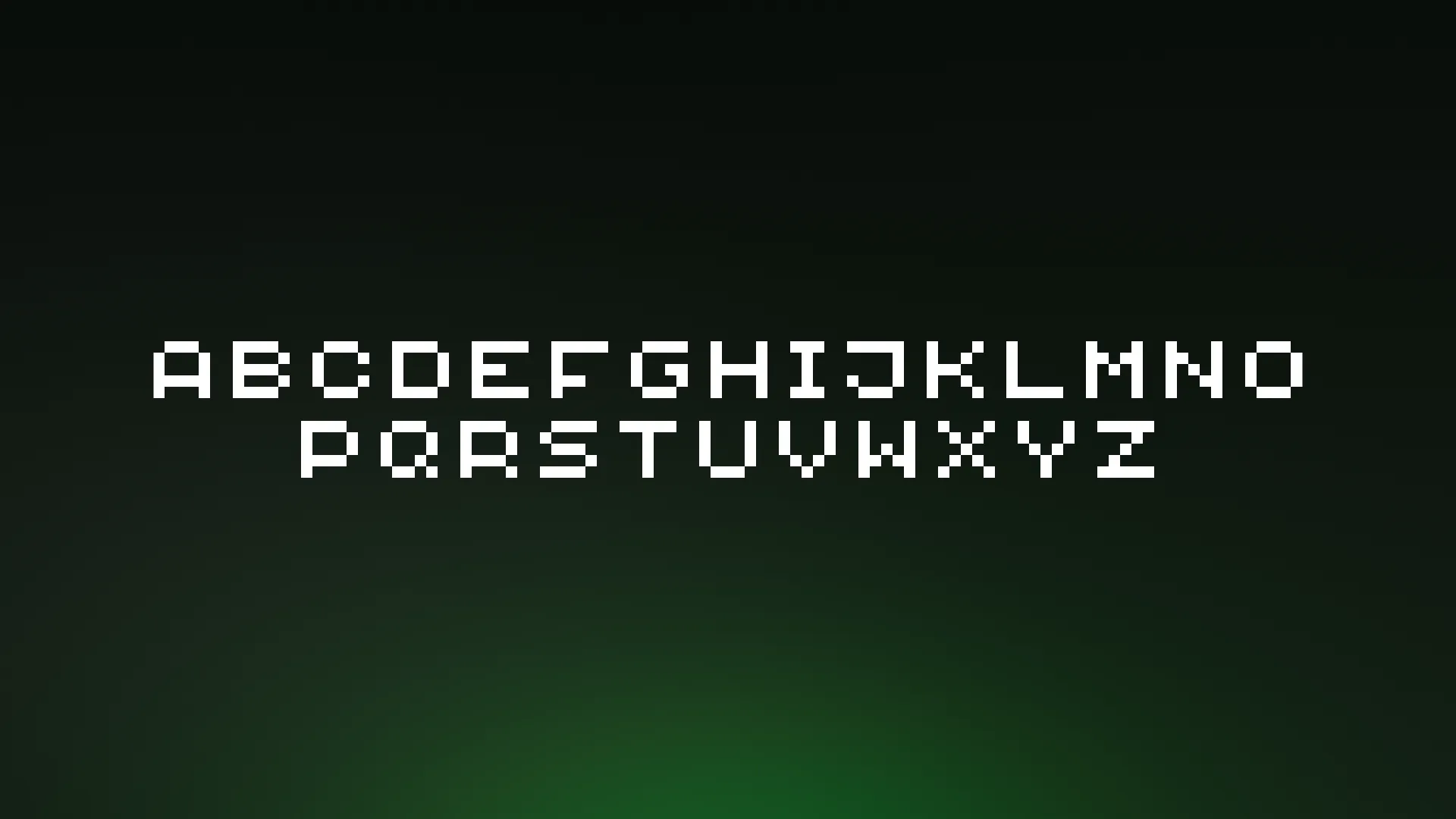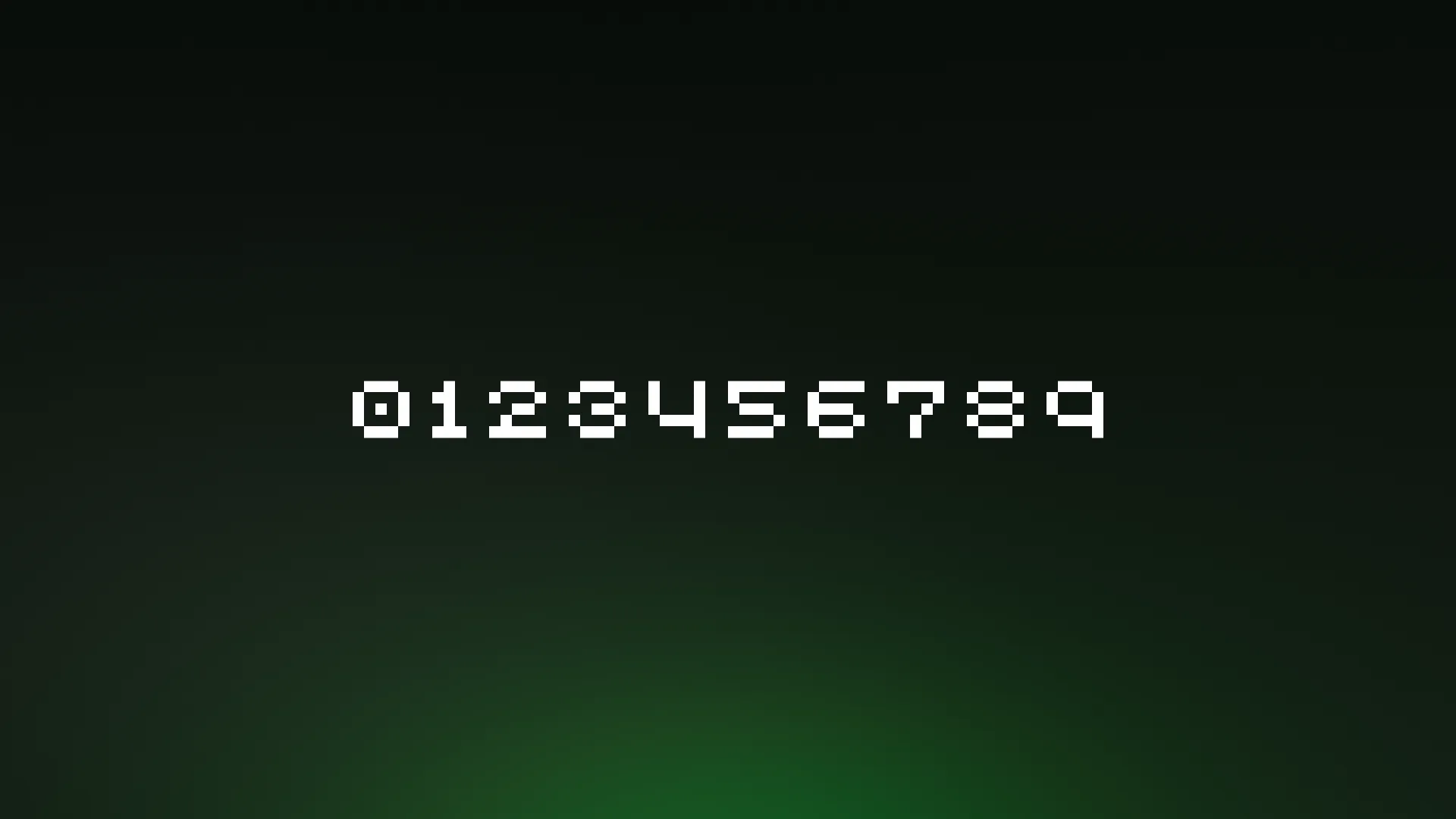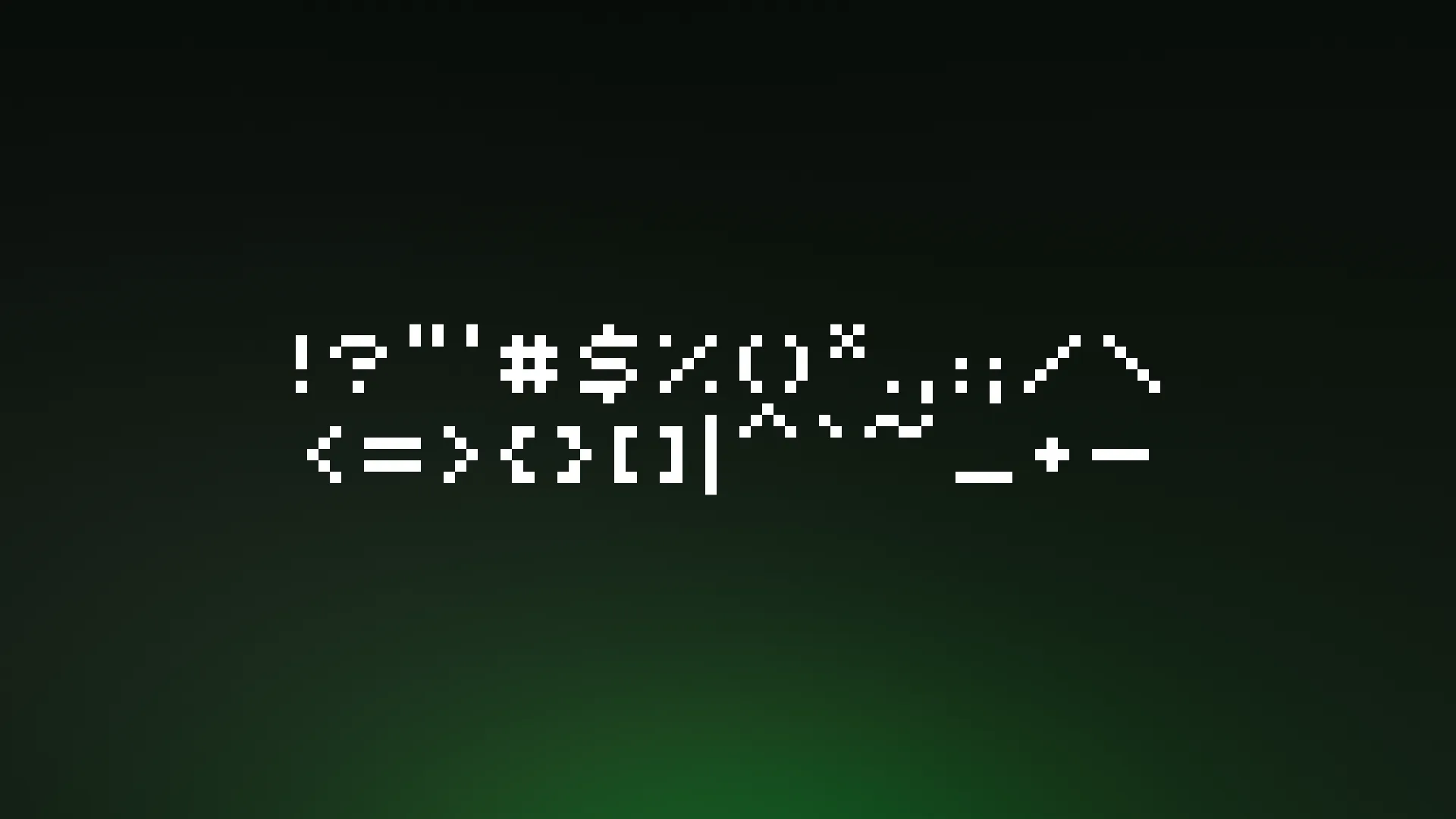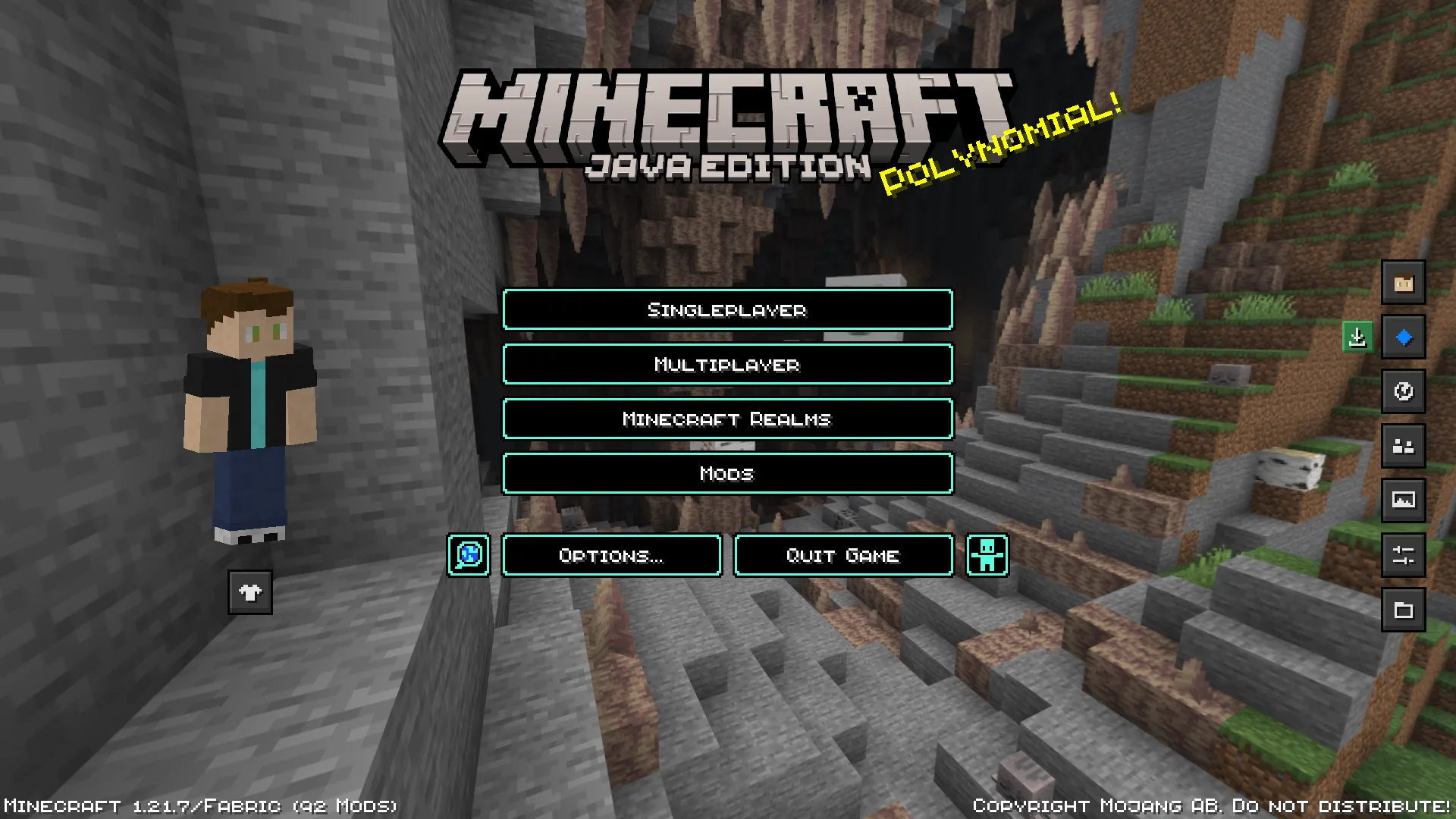
Small Caps Font
Этот ресурспак изменяет шрифт Minecraft на капитель. Включает улучшенные цифры, символы и знаки.
Ресурспак Small Caps Font заменяет стандартный шрифт Minecraft на капитель. Основное изменение касается визуального оформления текста в игре.
Пакет включает улучшенные цифры, символы и знаки по сравнению с аналогичными вариантами, уже присутствующими в ванильной версии. Изменения затрагивают только шрифт, не влияя на другие элементы игры.